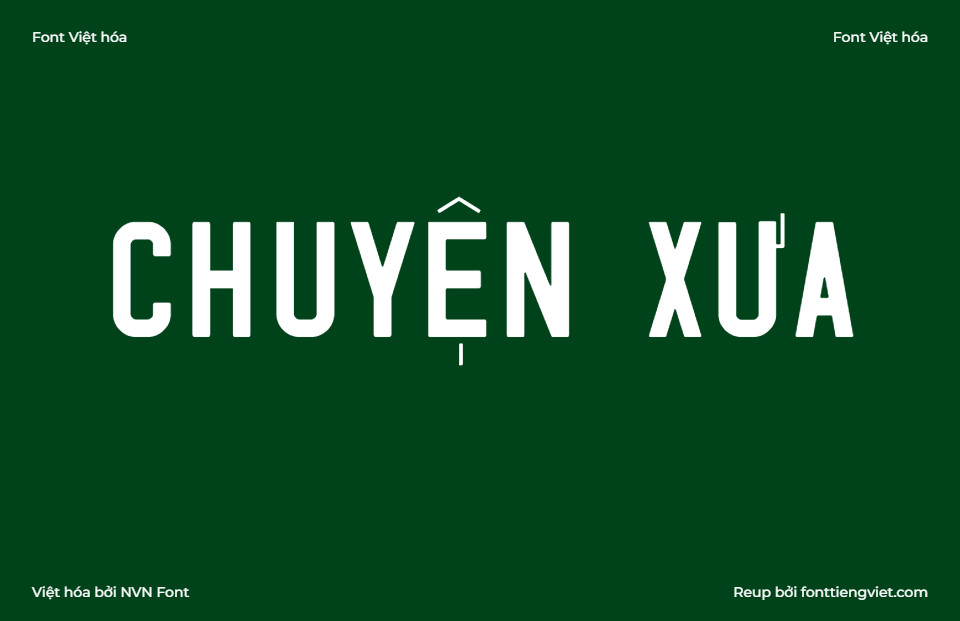
Font Việt hoá NVN Southland Sans Regular
Trong thế giới thiết kế đồ họa hiện đại, việc lựa chọn một bộ phông chữ vừa mang tính thẩm mỹ cao vừa đảm bảo tính ứng dụng là điều vô cùng quan trọng. Font Việt hoá NVN Southland Sans Regular nổi lên như một giải pháp hoàn hảo cho những ai đang tìm kiếm sự cân bằng giữa nét cổ điển và hơi thở đương đại. Đặc biệt, đối với các bạn học sinh và giáo viên, việc sử dụng một Font Miễn Phí chất lượng sẽ giúp các bài thuyết trình hay tài liệu học tập trở nên lôi cuốn và chuyên nghiệp hơn rất nhiều. Bộ font này đã được tinh chỉnh kỹ lưỡng để phù hợp hoàn toàn với bảng mã tiếng Việt, giúp loại bỏ các lỗi hiển thị dấu phổ biến.
Đặc điểm nổi bật của Font Việt hoá NVN Southland Sans Regular
NVN Southland Sans Regular không chỉ là một phông chữ không chân thông thường. Nó sở hữu những đường nét thanh mảnh, dứt khoát nhưng vẫn giữ được sự mềm mại cần thiết ở các góc bo tròn. Điều này giúp bộ font tạo ra một cảm giác thân thiện, dễ gần cho người xem. Khi sử dụng Font Việt hoá NVN Southland Sans Regular, bạn sẽ nhận thấy khoảng cách giữa các chữ cái được thiết kế cực kỳ hợp lý, giúp văn bản duy trì được sự thông thoáng ngay cả khi trình bày trong những đoạn văn dài.
Tính ứng dụng đa dạng trong giáo dục và đời sống
Với phong cách tối giản, font chữ này cực kỳ phù hợp cho việc thiết kế bìa sách giáo khoa, làm tiêu đề cho các báo cáo khoa học hoặc tạo ra các bảng tin trong lớp học. Sự rõ ràng của các ký tự giúp học sinh dễ dàng tiếp thu nội dung mà không bị mỏi mắt. Ngoài ra, các bạn trẻ có thể dùng nó để thiết kế áo lớp, làm thiệp chúc mừng hoặc tạo nội dung trên các nền tảng mạng xã hội như Facebook hay Instagram để tạo dấu ấn cá nhân riêng biệt.
Lý do bạn nên lựa chọn Font Việt hoá NVN Southland Sans Regular
Lý do đầu tiên chính là khả năng tương thích tuyệt vời. Bộ font này hoạt động mượt mà trên nhiều phần mềm thiết kế phổ biến như Adobe Photoshop, Illustrator cho đến các ứng dụng văn phòng quen thuộc như Microsoft Word hay PowerPoint. Việc cài đặt cũng vô cùng đơn giản, chỉ với vài thao tác chuột là bạn đã có thể sở hữu một công cụ thiết kế mạnh mẽ. Thứ hai, bản Việt hóa này đã tối ưu hóa toàn bộ các dấu thanh tiếng Việt, đảm bảo không có sự chênh lệch về độ cao hay độ dày giữa chữ cái và dấu.
Hướng dẫn sử dụng hiệu quả trong trình bày văn bản
Để tận dụng tối đa vẻ đẹp của Font Việt hoá NVN Southland Sans Regular, bạn nên kết hợp nó với các màu sắc trung tính hoặc pastel để tạo nên sự tinh tế. Nếu dùng làm tiêu đề, hãy tăng kích thước chữ và in đậm để tạo điểm nhấn. Ngược lại, khi dùng cho phần nội dung, hãy giữ kích thước vừa phải để đảm bảo tính dễ đọc. Việc phân cấp thị giác bằng cách kết hợp các biến thể của bộ font này sẽ khiến thiết kế của bạn có chiều sâu và chuyên nghiệp như được thực hiện bởi các chuyên gia thực thụ.
Kết luận về bộ font chữ quốc dân